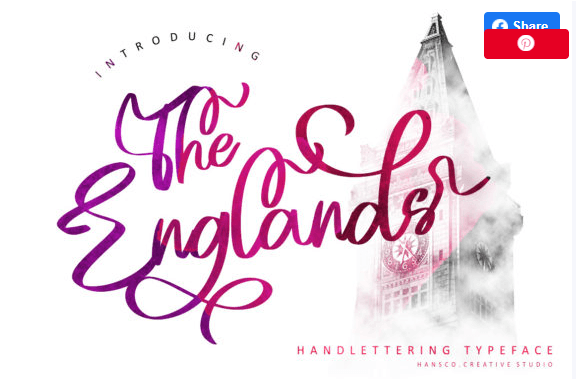
The Englands Font
Англия элегантна и причудлива, но также и аутентична. Этот универсальный шрифт для каллиграфии имеет широкий спектр применений, от дизайна до заголовков, и гарантированно добавит изысканности вашему следующему дизайну.
Этот шрифт имеет кодировку PUA, что означает, что вы можете легко получить доступ ко всем великолепным глифам и росчеркам! Он также имеет множество специальных функций, включая альтернативные глифы и лигатуры.